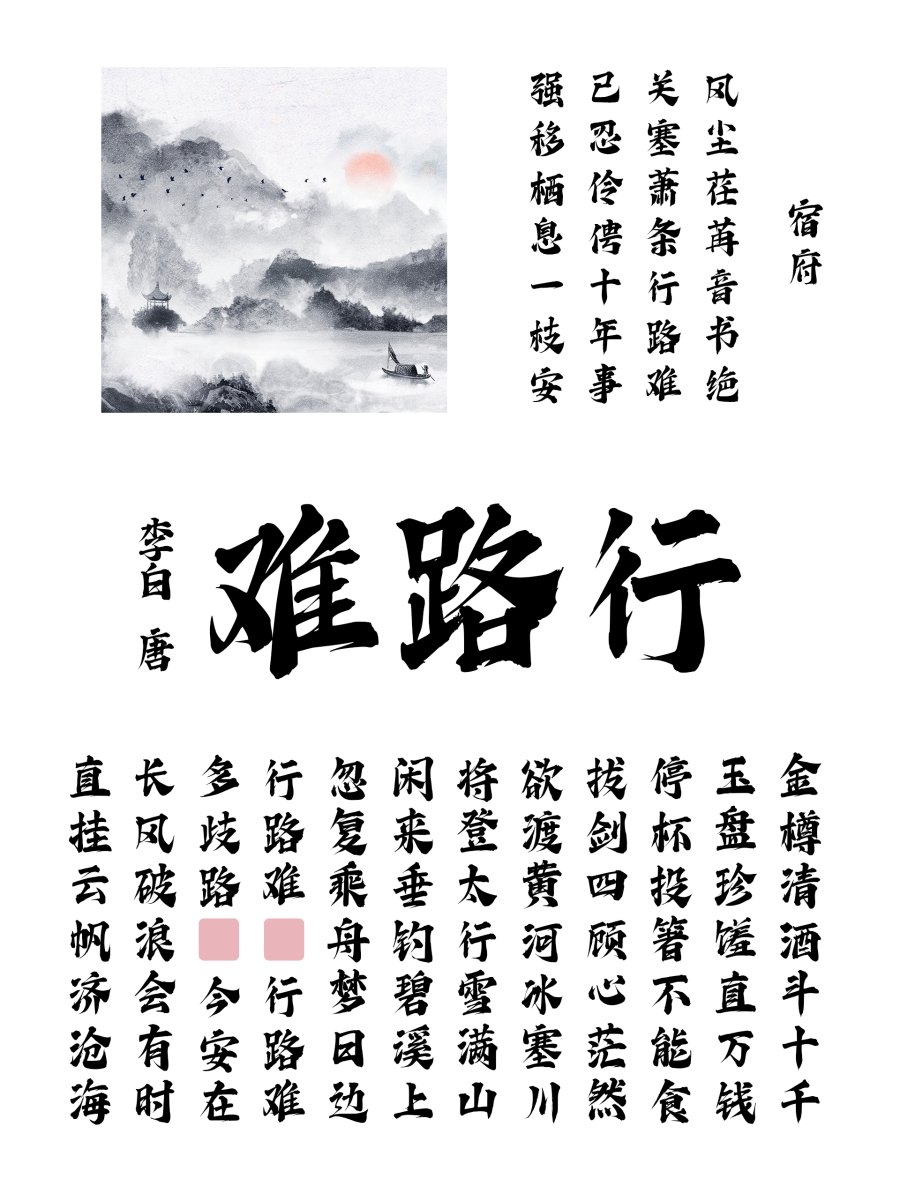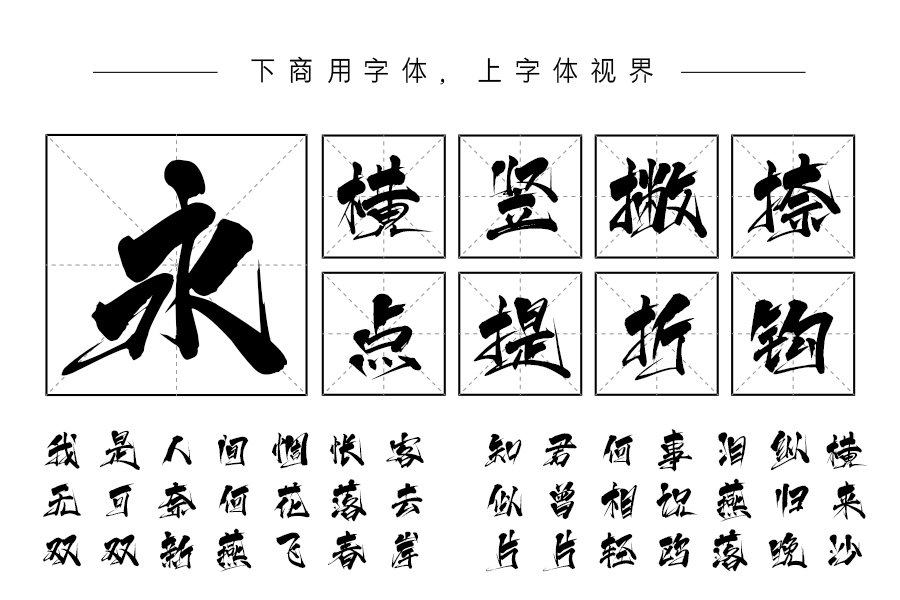
好看的中国风字体,你了解几款?
今天给大家分享两款好看的国风书法字体,真的太美了。
印品潮牌体,一款大气灵动的中国风毛笔字体,笔画饱满浑厚、又不失刚劲,牵丝连带的笔画显得字体浪漫洒脱,不仅有端庄大气,而且还有一种灵动的姿态。
印品潮牌体
上首逍遥书法体字体是一款手写书法字体,字体行云流水,落笔如云烟,笔势雄奇,姿态横生,其形独特,果敢进取,张扬乖张,看一眼会留下深刻印象,给人强烈的视觉冲击,符合现代年轻人的审美。
上首逍遥书法体